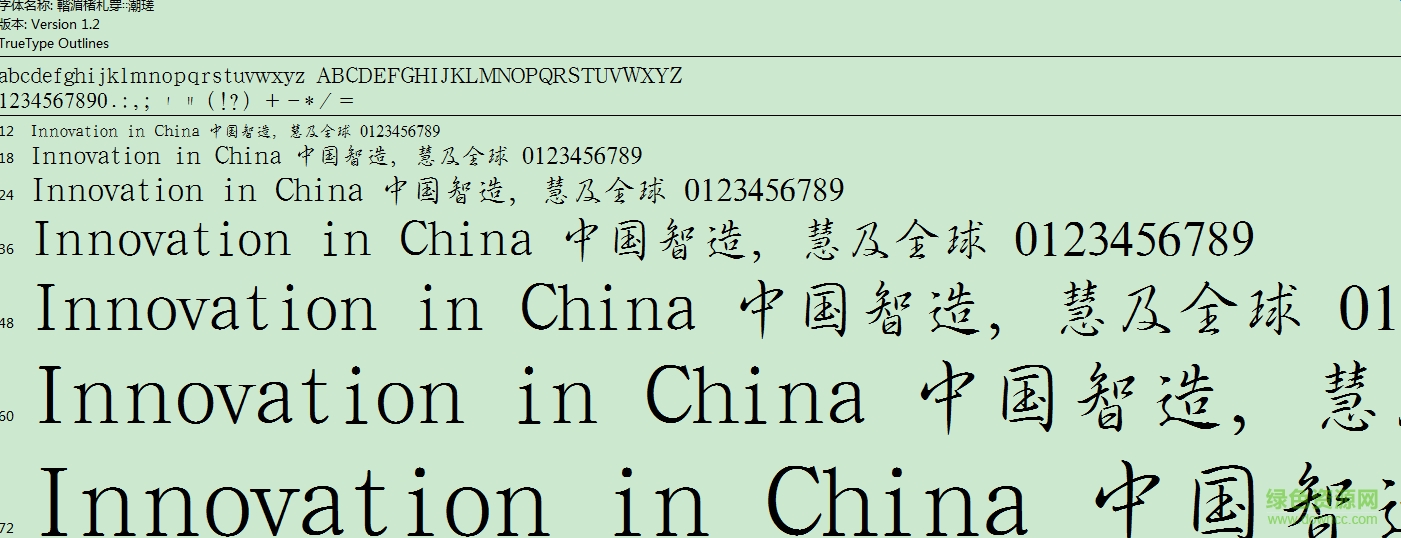
迷你簡(jiǎn)行書是一款行書字體的精簡(jiǎn)版本,書寫更加流暢耐看,適合用藝術(shù)策劃、廣告制作等方面。小編為大家提供免費(fèi)下載地址,有需要該字體的朋友可以來綠色資源網(wǎng)下載哦!
點(diǎn)畫活潑,體勢(shì)清朗,眉目清秀,體態(tài)大方,體現(xiàn)了啟體
點(diǎn)雅遒麗、超邁瀟灑的書法風(fēng)格,具有明快大方的特點(diǎn)。
字體取自“不激不厲,志氣平和”之意境,在結(jié)構(gòu)上富于
變化,在大起大落、跌宕起伏中尋求平穩(wěn),表現(xiàn)出書法字
體的寫意美。宜作廣告字體。
雖然是一款草書風(fēng)格的字體,但盡量保持字體原形,對(duì)筆
劃適當(dāng)減少,做到易學(xué)易識(shí),且融簡(jiǎn)、繁寫法于一體,匠
心私具??捎糜谖恼聵?biāo)題、廣告制作、裝飾、裝幀等。
婉轉(zhuǎn)嫵媚,溫順乖巧,極具表現(xiàn)力和親和力。非常適用排
印產(chǎn)品廣告和時(shí)尚刊物。